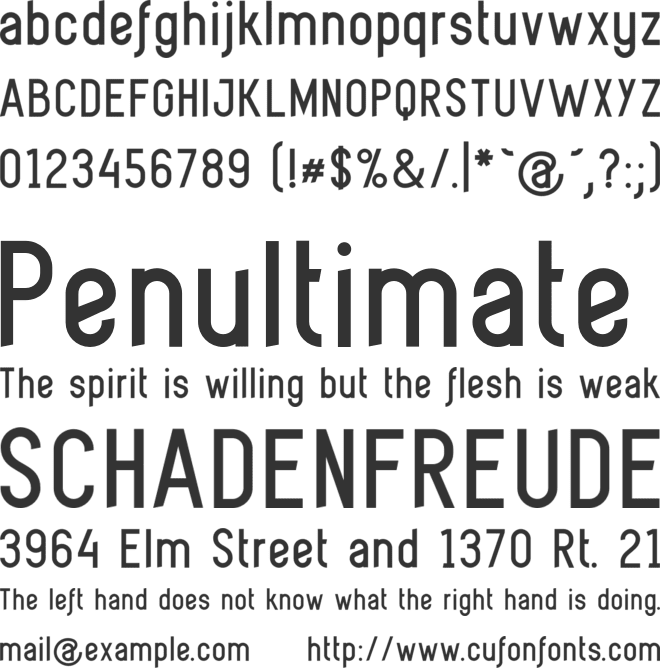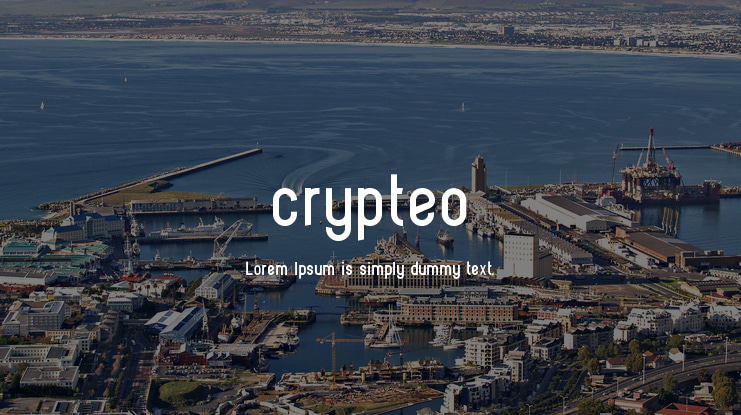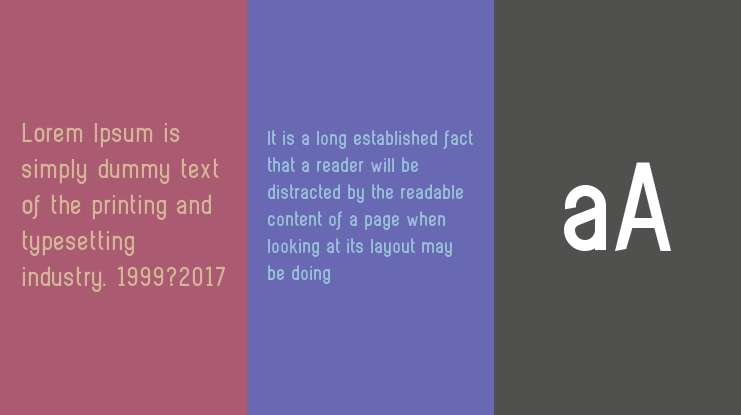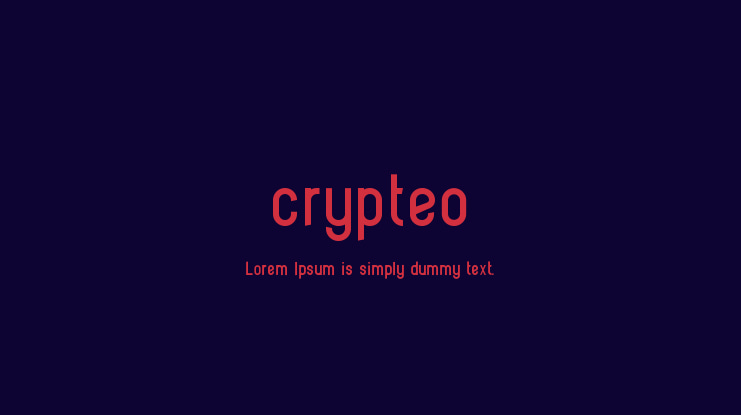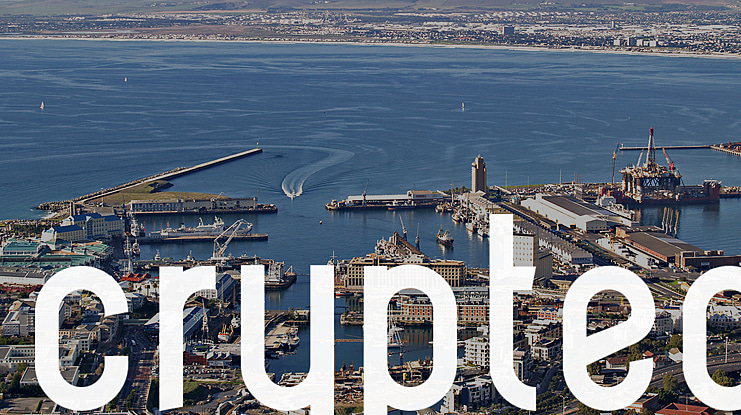
crypteo Font
UNE Il s'agit d'une typographie faisant partie d'une identité visuelle d'un lieu d'exposition historique. Elle devait à la fois être à la fois suffisamment lisible pour servir le propos des conservateurs du musée et suffisamment stricte et élégante pour contribuer à la théâtralité du lieu. Cette typographie est agrémentée d'un jeu de pictogrammes pour favoriser la signalétique. Voici donc ma troisième fonte maison.